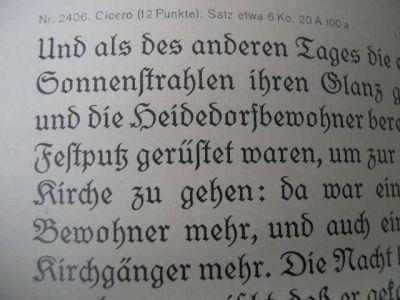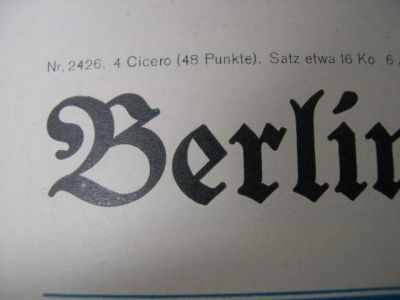
Das Dokument mit dem URI http://www.beepworld.de/members66/vau-ef-be/schriftliste1.htm zeigt ein Schriftmuster einer Bleisatz-Schrift mit dem Bezeichner "Buch-Fraktur, schmalfett". Diese ist offenbar eine Gebrochene Schrift von der Art Fraktur in dem engen Sinn der Klassifikation DIN 16 518. Entworfen wurde sie wohl von einer Person mit dem Namen "Buch". Ein Erstguß erfolgte, nach Aussage des oben genannten Dokumentes, um 1935 durch eine deutsche Schriftgießerei "Stempel" mit Sitz in Frankfurt am Main. Im WWW finde ich keine weiteren Hinweise auf diese Schrift.
Ich glaube, hier ist dem Kollegen Bernhard Schnelle ein Tippfehler passiert. Eine "Buch-Fraktur" ist bei Stempel nirgends gelistet. Auch im Schriftenverzeichnis der Schriftgießereien gibt es diesen Schriftnamen nicht (Namensrechte). Es gibt eine Buchdeutsch, aber die ist von Schneidler(?).
Was Bernhard hier zeigt ist die Buhe-Fraktur, entworfen vom Schriftentwerfer gleichen Namens zwischen 1910 und 1919. Und die wiederum ist in der Hauptprobe von Stempel von 1926 enthalten:
Eine solche Schrift paßt gar nicht ins Schriftenprogramm dieser Zeit - 1935. Gerade erst im Jahr zuvor, 1934, hat Stempel die Tannenberg, eine Neu-Gotische, aufgelegt.
Ob es die Buhe-Fraktur als digitalisierten Font gibt, ist mir nicht bekannt.
Es handelt sich um die Buhe Fraktur schmalfett (1935).
Es gab noch die
Buhe Fraktur (1915)
Buhe Fraktur halbfett (1915)
Buhe Fraktur fett (1922)
Entwerfer: Walter Buhe (1882-1958)
Digitaliserungen existieren bisher nicht.
Die "Buch-Fraktur, schmalfett" war von Interesse für mich als eine mögliche
Alternative zu "Bernhard-Fraktur, schmalfett". Beide Schriften gibt es bisher
nicht als Digitalisierung.